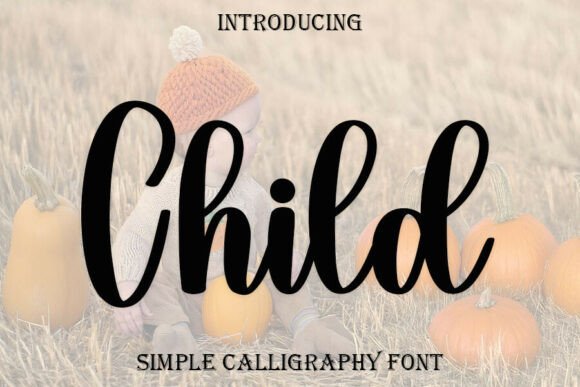
Child
Font enfant : Child, le nouveau titre pour votre créativité
**Un font manuscrit délicat pour un design unique
Vous recherchez un font qui saura s'imposer dans votre création artistique ? Alors vous êtes au bon endroit ! Le font Child est un excellent choix pour votre projet. Conçue avec soin, cette police d'écriture manuscrite délicate apporte une touche de originalité à votre design.
Utilisations multiples pour le font enfant
- **Lettres personnalisées** : Créez des lettres uniques et chaleureuses pour faire plaisir à vos proches.
- **Invitations spéciales** : Faites des invitations qui se détachent des normes avec le font Child.
- **Produits alimentaires** : Donnez une touche personnelle à vos produits alimentaires avec ce font délicat.
- **Titres d'articles** : Mettez en valeur vos titres avec ce font unique et captivant.
Avantages du font enfant
Le font Child offre plusieurs avantages qui en font un choix idéal pour vos projets créatifs :
- Unique et original
- Délicat et manuscrit
- Utilisable pour de nombreuses applications